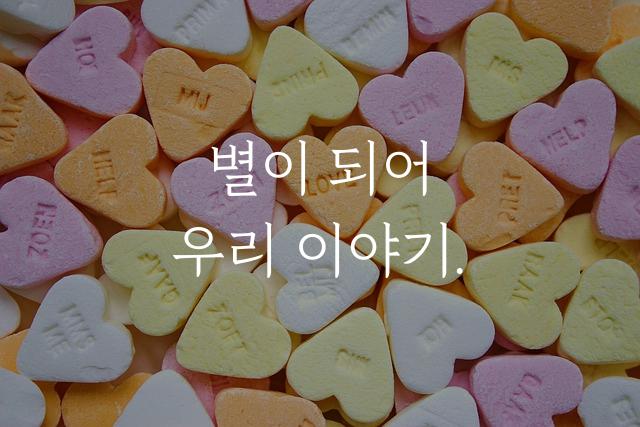
가평 물결은 윤디자인그룹과 가평군청이 협업하여 제작한 폰트로, 전통적인 장식체의 느낌을 현대적으로 재해석한 꼬인 글자와 물결 모양의 독특한 디자인이 특징입니다. 이 폰트는 시각적인 유동성과 동적인 감성을 강조하여 디자인에 풍부한 표현을 더합니다.
가평 물결은(는)
꼬임/입체감, 레트로, 장식 스타일, 감성적인, 게임 느낌, 별모양/패턴 계열의 생김새를 가지고 있으며
초대장, 인사말 카드, 일기/편지 등에서 자주 활용되며, 효과적인 메시지 전달에 적합합니다.
이 폰트는 라이프스타일, 문화/예술, 이벤트/웨딩 분야에 잘 어울리며,
친근한, 감성적인, 편안한 느낌을 담고 있는 것이 특징입니다.